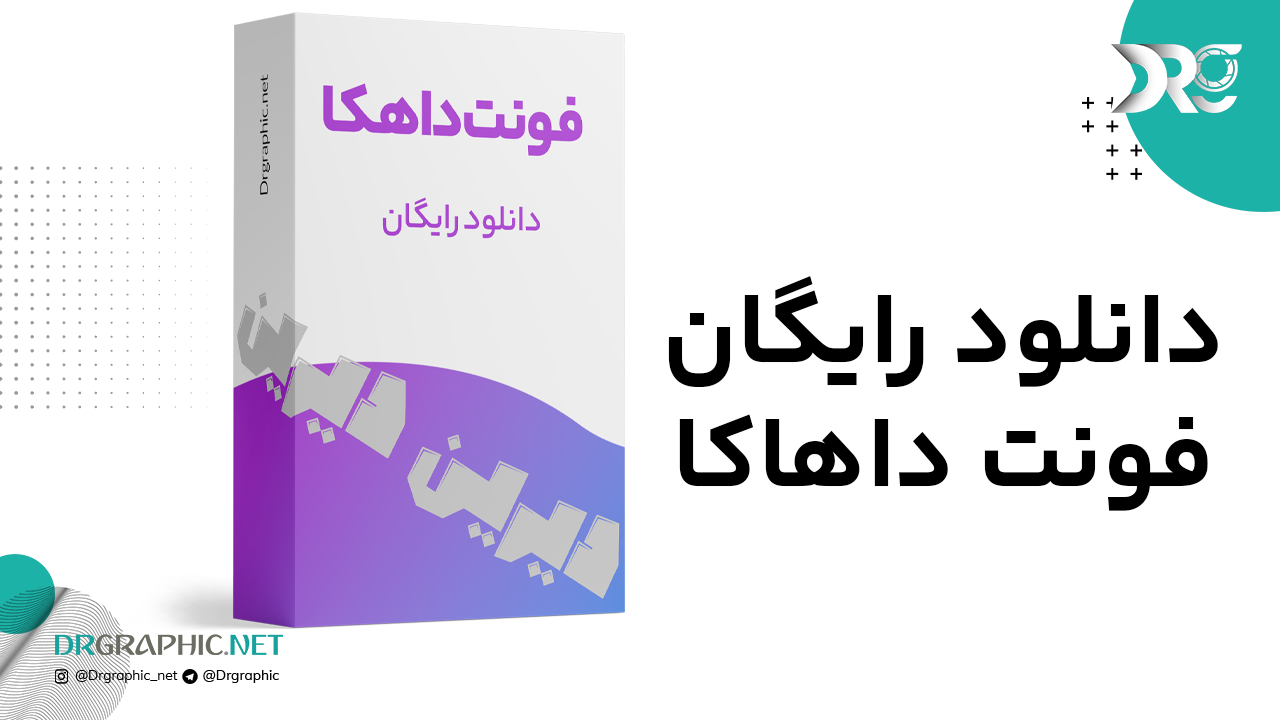
دانلود فونت دیرین دیرین (Dahka)
فونت عربی داهکا یا همان فونت دیرین دیرین یکی از بهترین فونت ها برای استفاده در عنواین و تایتل های گرافیکی می باشد .
فونت عربی دهاک
Dahka یک فونت پرمیوم و طنز آمیز عربی است که میتواند در بسیاری از طراحی ها تحت وب، طراحی های گرافیکی، لوگو و آرم ها، نام های تجاری، اپلیکیشن های متفاوت موبایل و … مورد استفاده قرار گیرد. قلم داهکا توسط تیم Arabic Font Store طراحی شده و با قیمت 22 دلار بفروش میرسد .
ویژگی های فونت Dahka
• طراحی دقیق و کاملا حرفه ای
• نمایش بی نقص تمامی حروف و اعداد بدون مشکل
• مناسب برای انواع طرح های گرافیکی
• مناسب برای ساخت و طراحی فونت، پوستر، لیبل و …
• مناسب برای نوشتن عناوین
• مناسب برای طراحی پوستر